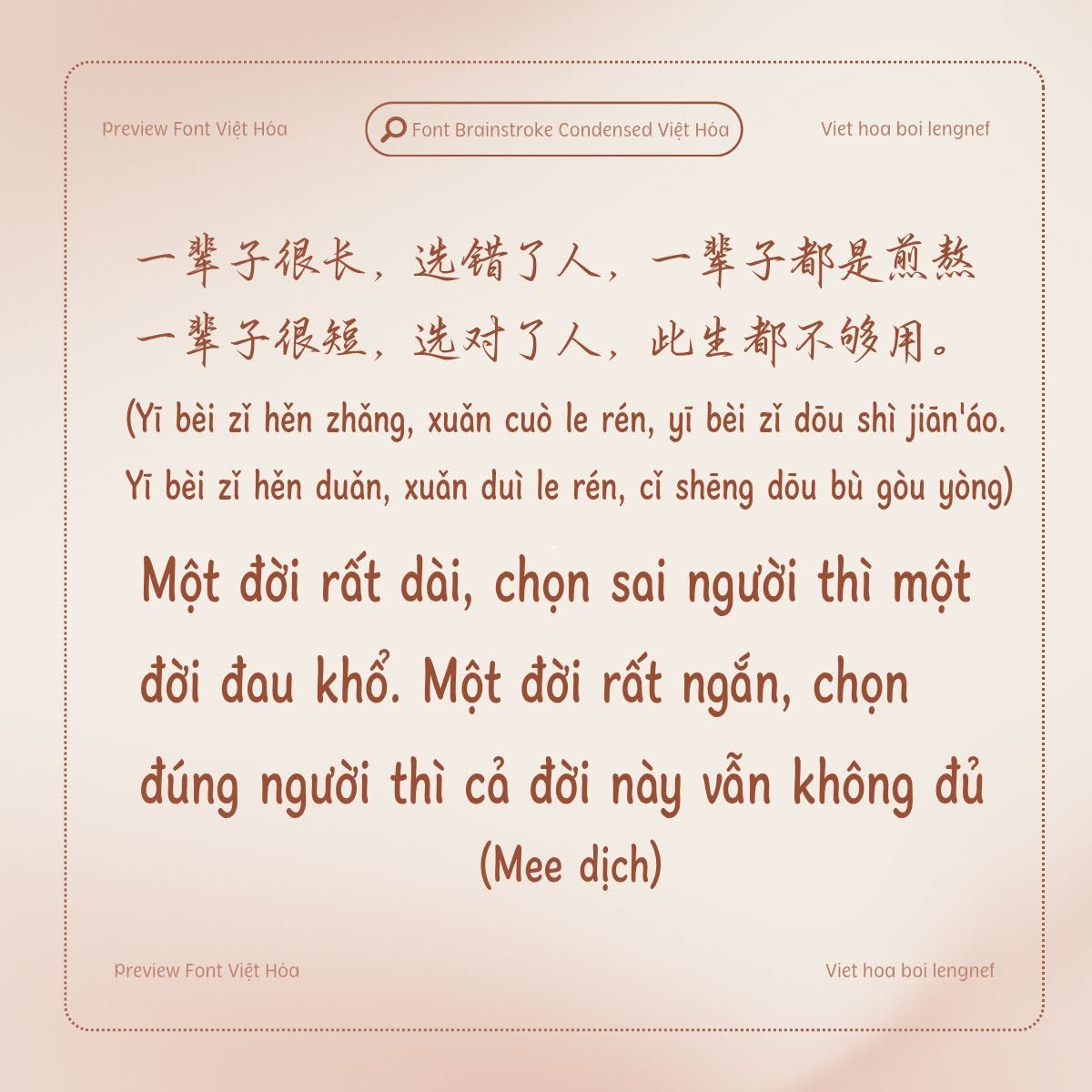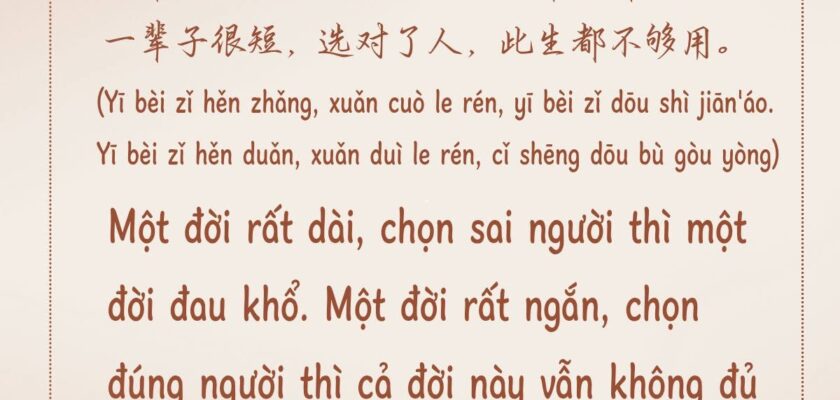
Share Font 82 || LF Brainstroke Condensed
- Tác giả: Graham Meade
- Việt hóa: lengnef
Brainstroke Condensed là kiểu phông chữ viết tay gọn gàng, dễ thương, dễ nhìn. Bộ font này có 14 style nhưng chỉ Việt hóa condensed.